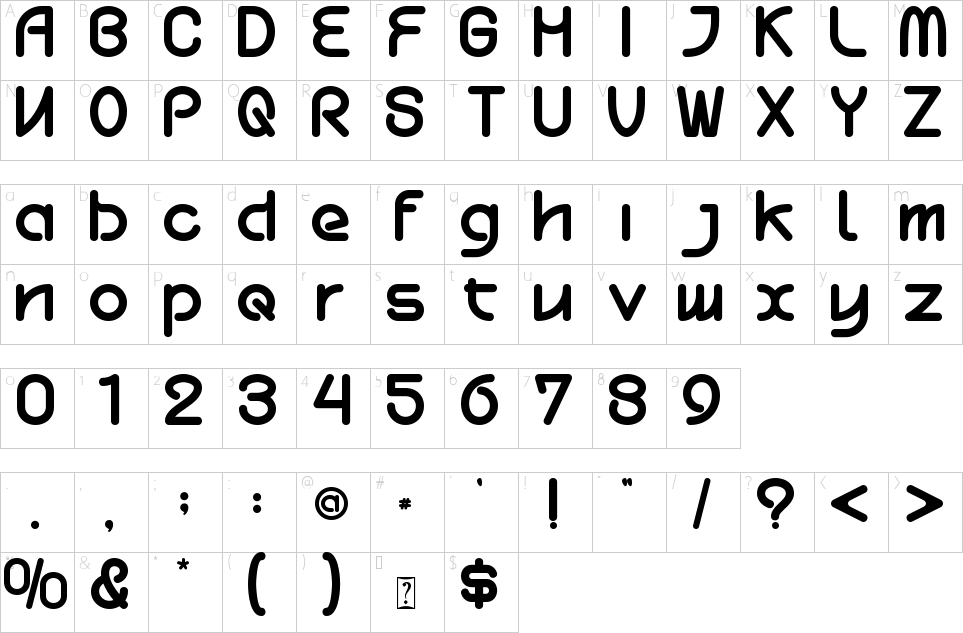
A fonte Axaria é uma grata surpresa para os designers de qualquer nível. Desenhada pelo Letterara Studio, ela oferece um charme elegante que combina elegância e simplicidade, ideal para criar designs envolventes e naturais. Este é um recurso gráfico gratuito que não apenas enriquece seu trabalho, mas também economiza tempo, pois você não precisa se preocupar com os direitos autorais. Com mais de 357 downloads, é evidente que a Axaria font já ganhou o reconhecimento de designers de todo o mundo. Seja você um estudante ou um profissional, Axaria é uma ótima escolha para adicionar um toque único a seu trabalho. Não hesite em experimentar a Axaria font para experimentar o seu próprio poder.